»Eines der sprechendsten Ausdrucksmittel jeder Stilepoche ist die Schrift. Sie gibt nächst der Architektur wohl das am meisten charakteristische Bild einer Zeit und das strengste Zeugnis für die geistige Entwicklungsstufe eines Volkes. Wie sich in der Architektur ein voller Schein des ganzen Wogens einer Zeit und äußeren Lebens eines Volkes widerspiegelt, so deutet die Schrift Zeichen inneren Wollens. Sie verrät von Stolz und Demut, von Zuversicht und Zweifel der Geschlechter.«
Peter Behrens begleitete mit diesen – aus heutiger Sicht pathetischen – Worten die Publikation seiner 1901 erschienenen Schrift, die neben der von Otto Eckmann wesentlich zur Erneuerung der Schriftkultur in Deutschland beitrug. Diese Erneuerung war Ergebnis von Debatten um den ästhetischen Verfall zeitgenössischer Druckerzeugnisse und hatte Fragen nach nationaler Identität und Weltöffnung, nach Zweckbestimmung und Lesbarkeit neu entfacht. Inzwischen wissen wir, dass Schrift sehr wohl auch etwas über das äußere Leben eines Volkes mitteilt und dass zwischen Stolz und Demut die Zweifel und Gewissheiten auch von Liebe, Vorschriften, Aufruhr, Hass und Provokation, Spiel und Witz getragen sein können.
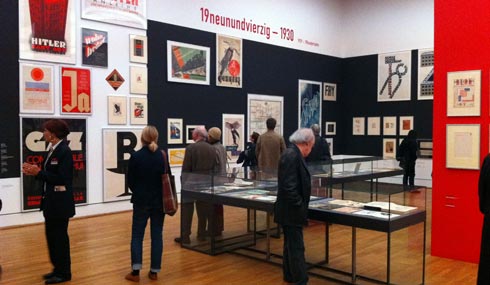
Die Ausstellung »Welt aus Schrift« (Sonderausstellungshallen Kulturforum, am Potsdamer Platz, Berlin) widmet sich seit heute der Entwicklungsgeschichte unserer Schrift. In chronologischen Schritten wirft die Ausstellung mit über 600 Exponaten ihre Schlaglichter auf die typografischen Revolutionen des 20. Jahrhunderts, die Interaktion von Schrift und Bild und die vielfältigen Wechselwirkungen zwischen freier und angewandter Kunst.
In der Chronologie von insgesamt sechs Doppeljahrzehnten zeigt »Welt aus Schrift« schlaglichtartig nachhaltige Entwicklungen und Zäsuren in den letzten 120 Jahren, sowie parallele zum Teil kontroverse Erscheinungsformen und macht die belebenden Wechselwirkungen von freier und angewandter Kunst sichtbar. Beginnend mit Beispielen der englischen und amerikanischen Buchkunstbewegung um William Morris und Will Bradley, mit Plakaten und Drucksachen von Henry van de Velde, Theo van Rysselberghe, Henri Privat Livemont und Pierre Bonnard als Vertreter des belgischen und französischen Art Nouveau, frühen Drucksachen der Wiener Sezession von Alfred Roller und Koloman Moser oder Beispielen der deutschen Jugendstil- und Werkbundbewegung (Otto Eckmann, Peter Behrens, Fritz Helmuth Ehmcke, Lucian Bernhard) zeigt die Ausstellung in einem zweiten Kapitel unterschiedliche Wege des Schriftplakates von streng sachlicher und konstruktiver bis zur bildhaften Verwendung von Schrift. Glanzstück der Ausstellung ist das von Boris Bilinsky entworfene Plakat für die französische Aufführung des Films »Metropolis« von 1927. Darüber hinaus sind Buch-, Zeitschriften und Akzidenzdrucke von den Dadaisten und italienischen Futuristen zu
Ausstellung und Katalog widmen sich ausführlich den Jahrzehnten nach dem Zweiten Weltkrieg, als die Vorkriegsmoderne wieder an Einfluss, besonders in der Schweiz und den USA. Armin Hofmann, Emil Ruder oder Karl Gerstner stehen für den sog. Swiss Style, der nicht zuletzt durch die serifenlosen Groteskschriften Helvetica (von Max Miedinger) und Univers (von Adrian Frutiger) eine internationale Ausstrahlung bekam. Die 1950er und 60er Jahre prägen auch die Niederländer Willem Sandberg und Pieter Brattinga sowie die Italiener Vignelli und Cresci. Visuelle und Konkrete Poesie beeinflusste die Grafik der 1960er Jahre (Wolfgang Schmidt und Christian Chruxin), ebenso die Typografie von Herb Lubalin und Willy Fleckhaus.
Neben konstruktiver Grafik behaupteten sich immer auch spielerische, hintersinnige Bildhaftigkeit und Dekonstruktion, die auf ungewöhnliche Lesarten setzten und sich gegen die Präsenz fotografischer Bilder behaupteten. Daneben gewann die Pop-Kultur Einfluss auf die Grafik. Schließlich revolutionierte seit den späten 1970er Jahren die Musikkultur von Punk und Techno die Schriftbilder, was in Zeitschriften Ray Gun, Emigre, Face, Rolling Stone, Frontpage oder Plattencover der Sex Pistols deutlich wird.
Schließlich zeigt sich in den jüngsten Beispielen eine neue Offenheit gegenüber historischen Leistungen der Typografie, eine stärkere Formenklarheit bei gleichzeitiger Betonung des Subjektiven. Ergänzend werden Filme gezeigt und Projektionen, die den Blick auf Schriften im Stadtraum lenken, das Feld der bewegten Schriften berühren und schließlich einzelne Typografen vorstellen.
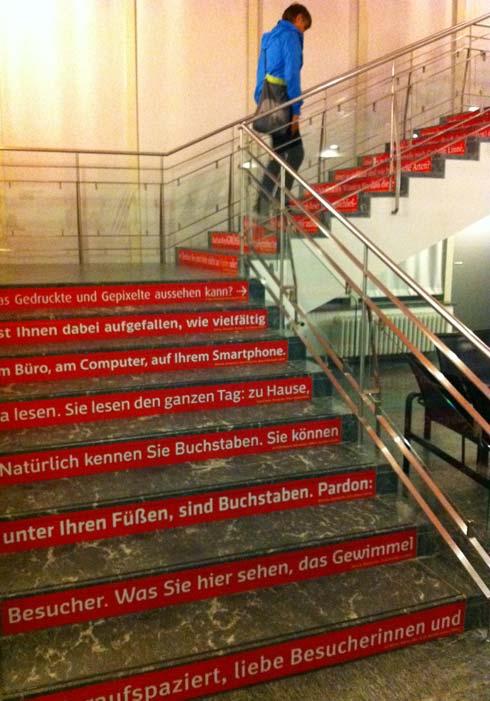
Wie bereits am Montag erwähnt, wurde FontShop von der Kuratorin Anita Kühnel eingeladen, das die Ausstellungsräume verbindende Treppenhaus zu gestalten (siehe auch: »Welt aus Schrift« öffnet morgen). Zu diesem entwarf FontShop eine Treppen-Installation, bei der die Vorderflächen der Stufen mit Schriftmustern gestaltet wurden. Jede der 6 Treppen repräsentiert eine Schriftklasse, als da wären Sans Serif (8 Stufen), Serif (10 Stufen), Slab Serif (6 Stufen), Script (6 Stufen), Display (8 Stufen) und Blackletter (6 Stufen). Die Einteilung entspricht der des FontBooks und spiegelt sich auch in der iPhone-App FontShuffle wider. Ein launiger Mustertext soll geduldigen Lesern die Augen für die Vielfalt der Schriftenwelt öffnen.
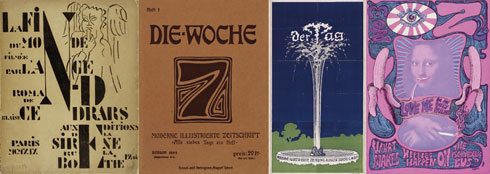
ich hoffe nicht dass das entgültige Druck-PDF war ;-)
bei Treppe 6 – zeile 1 – steht Glypha – Adrian Frutiger…
Sehr aufmerksam, ist auf der Originaltreppe richtig:
FF Karo, Entwerfer: Martin L’Allier (2005).
Ich korrigiere aber das PDF gleich noch mal. Danke. Das PDF wurde als Klebeplan für den Monteur erstellt und ging nicht in die Schlusskorrektur.
Danke für den Hinweis mit dem Ausstellungskatalog. Den werde ich mir bestellen. :)
Ich frage mich gerade ernsthaft was ich aus dem Cover des Kataloges herauslesen soll. Das einzige das ich lesen kann ist WELT. Aber ich bin mir sicher das steckt mehr dahinter. Jemande eine Idee?
ich vermute, das Fragmente von Schrift-Positivformen hier die Negativräume von WELT bilden- das wars dann auch schon ;)